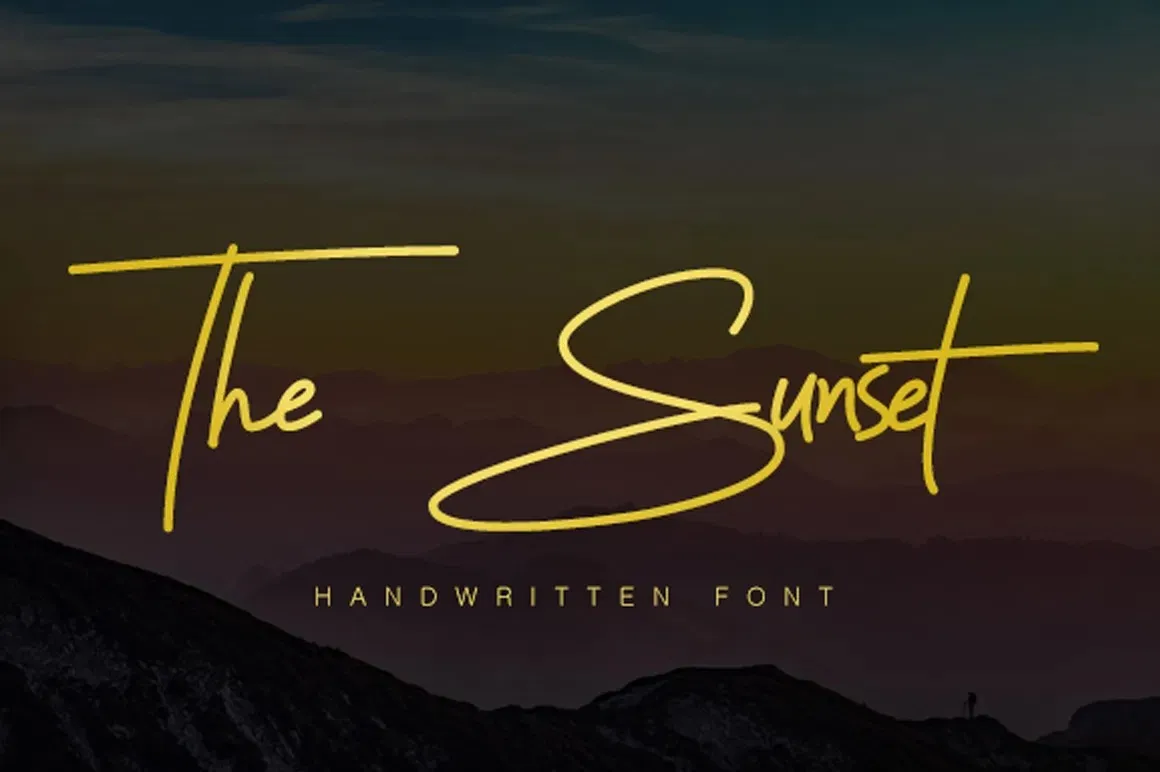
The Sunset Font – Download Grátis
A fonte “The Sunset Font” é uma escolha perfeita para quem busca algo elegante e autêntico na sua próxima criação visual. Cada letra deste script foi esculpida com mão, transmitindo um estilo natural e limpo, com linhas de traço monocromático que se curvam em ângulos atraentes e desenhos coloridos. Esta font é especialmente adequada para o design de logotipos, marcas sociais, subtítulos para filmes, títulos de livros, até mesmo textos longos, oferecendo um tom suave que se combinaria perfeitamente com tipografia sans-serif ou serif. Com alternativas minúsculas e ligaturas disponíveis, você pode personalizar ainda mais a aparência da sua fonte. Este é um recurso indispensável para designers de gráficos em busca de uma solução visual única e elegante.